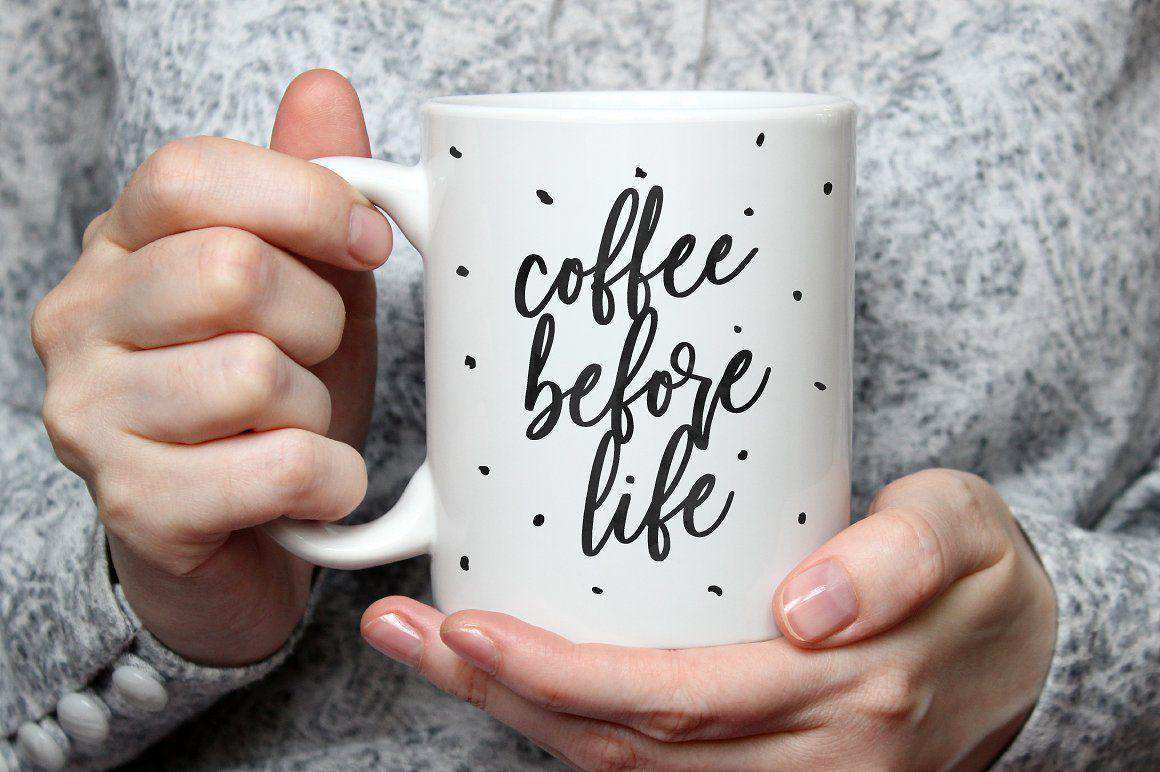
介绍全新漂亮的BloomType字体。它是一种完全交替(大写和小写)的纯正字体。设计为完美结合了多种标志,如活力、网站徽标、,Instagrampost和许多名字?介绍了一种全新的漂亮的BloomType字体。它是一种具有完全交替(大写和小写)的独特字体和字母字体。设计为能够完美地在多个标志中工作,这些标志结合了维景、网站徽标、Instagrampost和许多名字?